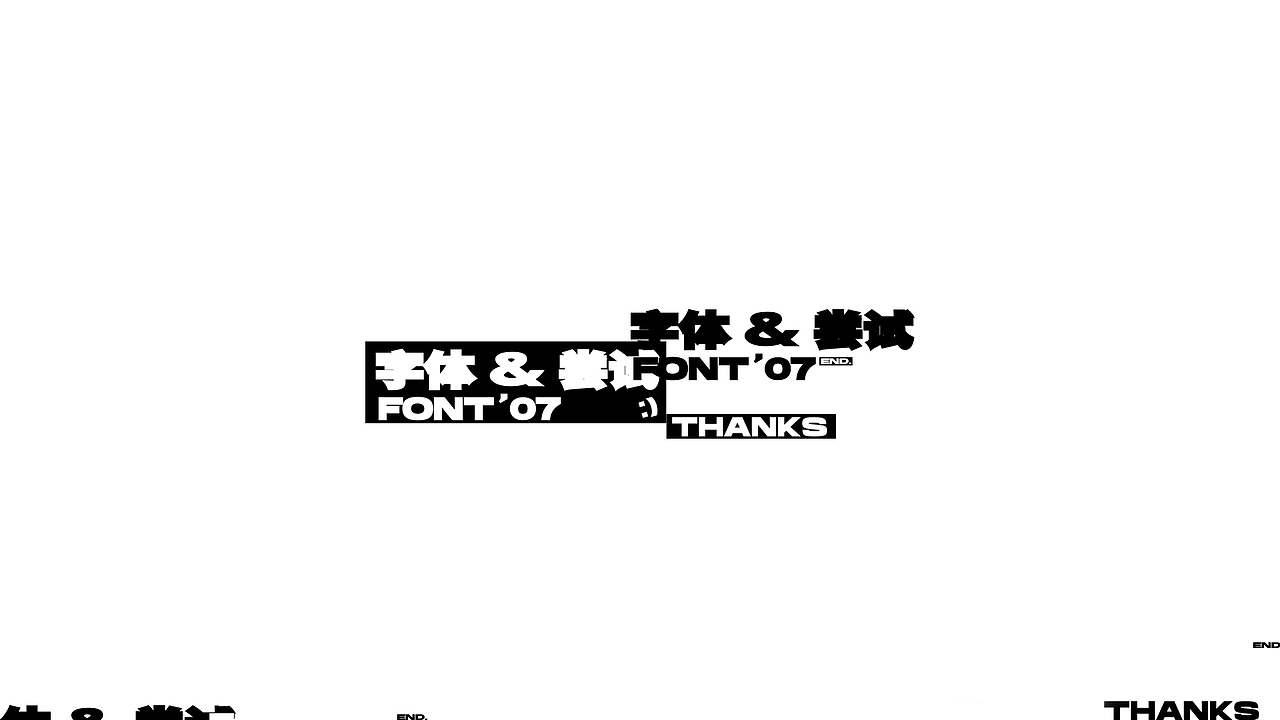
字体&尝试 | FONT ' 07
近期的一些字体练习,业余时间探索了一些字体形式感上的东西,比较少做的不多,也不知道下一个贴啥时候能攒够啊哈哈~
接触字体也快两年了,期间断断续续的没有一直去做,总是兴起而做兴致而终,算是自娱自乐。大多字都是凭自己感觉做的,对字型理解还是不够透彻(好奇怪这话好像在一年前说过:)